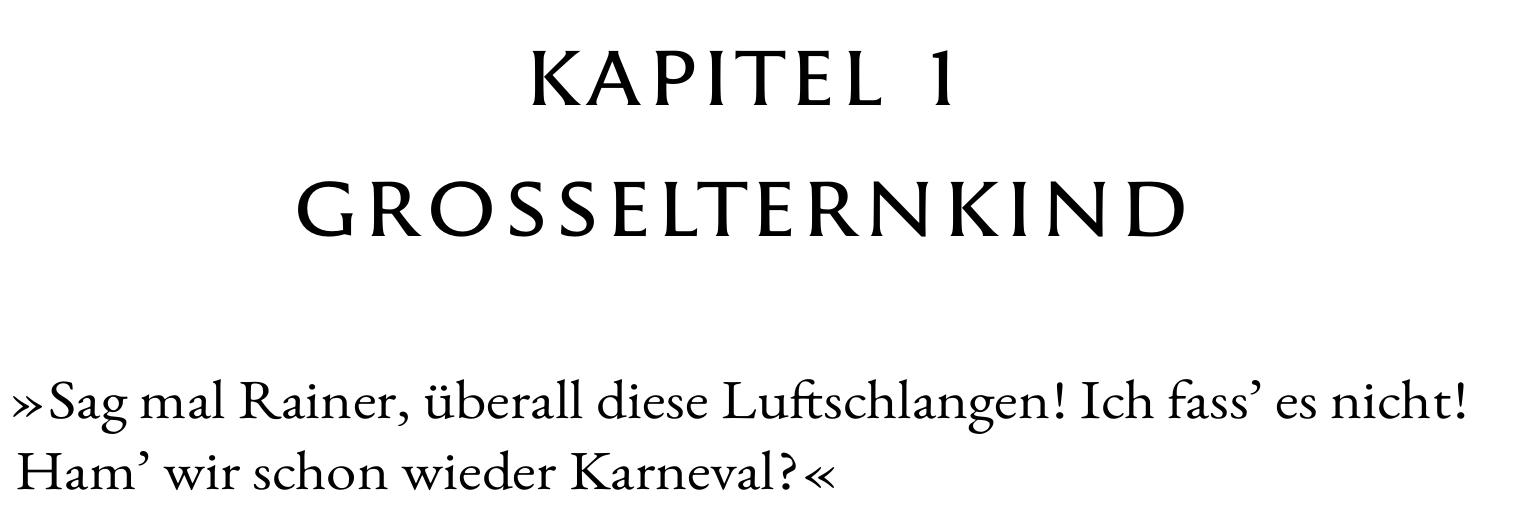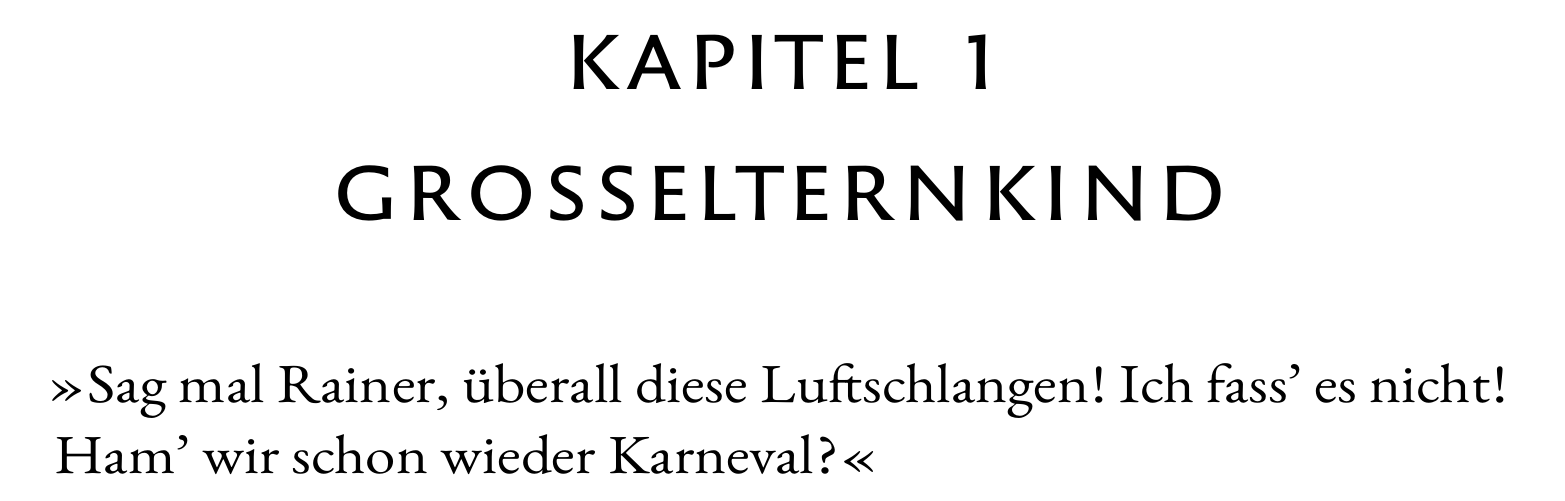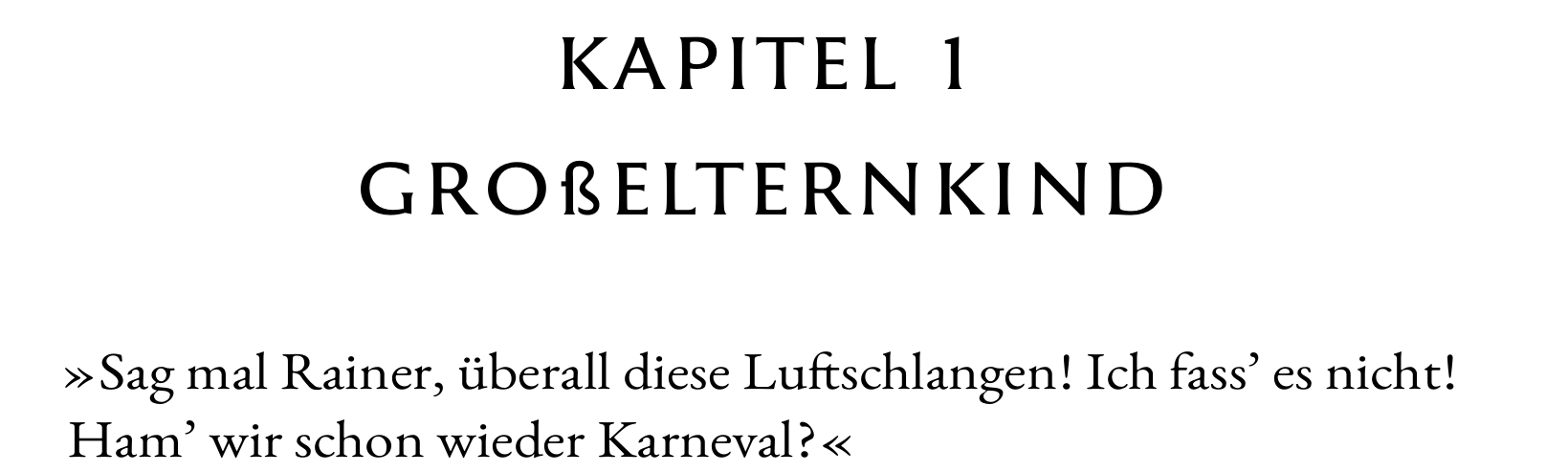
Schriftmischung Reforma 1969 und Garamond
Ich habe mal eine Frage an die Experten. Ich habe gerade mal einen Layoutversuch gemacht. Es geht um einen belletristischen Buchtext, der in EB Garamond gesetzt ist. Normalerweise würde ich jetzt auch die Kapitelüberschriften etc. in der EB Garamond setzen, aber ich wollte mal einen Versuch machen und habe die Flare-Serifenschrift Reforma1969-Gris für die Überschriften genommen. Und jetzt die Frage aller Fragen: Passt das?
Mir tun bei dem Anblick nicht die Augen weh. Aus meiner Sicht ist die Reforma, die ich bewusst in Versalien und größer einsetze, als Flare-Serifenschrift von der Garamond »weit genug weg« um sich nicht zu beißen.
Aber ich bin gerne bereit, mich von Experten eines besseren belehren zu lassen - allein schon, um mein Auge zu schulen.
Danke für den Hinweis. Ich hatte naiv angenommen, die Schrift habe ein Versal-ß ohne es nachzuprüfen. Nur eine neugierige Frage zurück: Woran hast Du erkannt, dass es kein Versal-ß ist? Kennst Du die Schrift? Oder machst Du das an Proportionen fest?
Wie sieht es sonst generell mit der Mischung aus? Ich sehe nichts, was gegen die Kombination der Schriftarten spricht, lasse mich aber gern eines Besseren belehren.
Gegenfrage: Spricht etwas dagegen für den Fließtext die zur Reforma noch besser passende Serifen-Version zu verwenden?
Wenn eine Schriftdesign schon mehrere Stile enthält, könnte man das ja nutzen. 😉
Für Konsultationstexte könnte man dann sogar noch die Reforma 2018 in Betracht ziehen.
Außerdem sei auf die schönen Ligaturen verwiesen, die Deinen Überschriften noch etwas visuelle Würze geben könnten.
Nein, überhaupt nicht. Das hatte ich auch schon ausprobiert (ich nutze LaTeX, da ist sowas vergleichsweise schnell implementiert). Das Beispiel, das ich gepostet habe, war mehr Spielerei. Ich wollte gucken, ob es passt und habe nichts gefunden, was dagegen spricht. Aber da ich kein ausgewiesener Typograph bin und weiß, dass der Teufel im Detail liegt, wollte ich Expertenrat haben - allein schon, um daraus zu lernen.
Woran hast Du erkannt, dass es kein Versal-ß ist?
Wie Phoibis schon geschrieben hat: Es ist im Vergleich mit den anderen Versalbuchstaben viel zu schmal. Und die obere Rundung scheint mir auch etwas höher als bei den anderen Buchstaben mit einer Rundung zu sitzen.
Woran hast Du erkannt, dass es kein Versal-ß ist?
Man kann es auch daran erkennen, wie und ob in der Glyphentabelle entsprechende Slots belegt wurden. Die Reforma wurde ursprünglich nicht mit einem ẞ ausgestattet. Es ist aber gut möglich, dass es bei Updates der Fontfamilie ergänzt wurde/werden wird.
Ich habe dann auch in die Glyphentabelle geschaut und gemerkt, dass in der Tat das Versal-ß fehlt. Deswegen musste man das Ganze umbasteln, was mich ein bisschen Frickelei mit Lua gekostet hat, bei der ich aber mal wieder was gelernt habe.
Jetzt sieht es so aus:
Und nochmal die Frage an die Experten: Kann man das machen oder sollte man das lassen?
Die Schriftmischung kann man so machen, denke ich (Du solltest ggf. noch mal Gewichte gegenüberstellen und im Ausdruck vergleichen – am Bildschirm wirkt der Fließtext-Schnitt zumindest etwas hell). Wenn Du noch mehr Kontrast erzeugen willst (das ist meistens der sicherere Weg), nimmst Du die Reforma 2018 für die Headlines.
Aber ich finde alles in der Reforma-Familie gesetzt wäre noch eleganter gelöst – vorausgesetzt deren Zeichenrepertoire ist für Deinen Anwendungsfall ausreichend. 😉
Wenn Du willst, kannst Du einfach ein paar Varianten setzen und diese hier zum Vergleich nochmal posten.
Danke für den Tipp. Das ist in der Tat ein interessanter Überblick.
Die Reforma 1969 ist nun natürlich als Flare-Serifenschrift ein bisschen zwischen den Stühlen. Auf keinen Fall Grotesk, aber eben auch keine "echte" Antiqua.
Mein eigener Eindruck ist aber, dass durch die abweichende Größe und den Versalsatz genügend Abstand zur Garamond besteht.  Aber allein der Umstand, dass ich das falsche ß übersehen habe, zeigt, dass mein Eindruck nicht das Maß aller Dinge ist.
Mein eigener Eindruck ist aber, dass durch die abweichende Größe und den Versalsatz genügend Abstand zur Garamond besteht.
Ja, wie gesagt das passt so und man sollte bei der Schriftwahl auch den Inhalt nicht ganz außer Acht lassen. Vielleicht ist eine Flare da sogar stimmiger als eine Sans.
Mit anderen Worten: Ihm war die Schrift im Grunde zu dünn? Das Problem ist aber wahrscheinlich nur durch einen Wechsel der Schrift zu lösen, oder?
Tendenziell zu dünn, ja. Aber das kann gedruckt auf dem Papier auch passen. Man sollte es sich nur genau ansehen und ggf. mit einem nächst dickeren Schriftschnitt vergleichen.